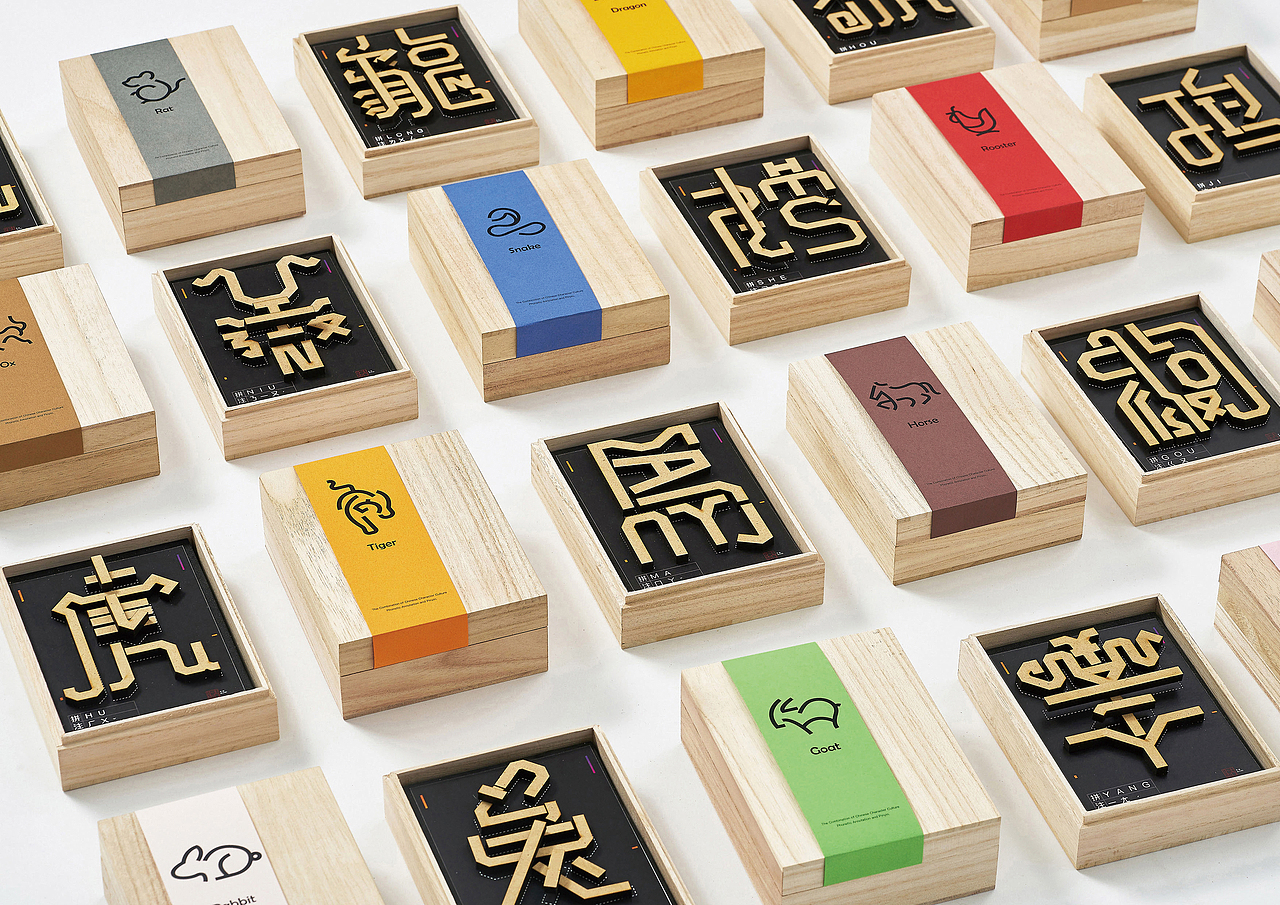
-透过文字再设计呈现两岸文化的连接与包容
We show cross-strait cultural connection and inclusiveness through ideogram redesign.
汉字在中国大陆与台湾之间不仅存在简繁字型之分,其分别所使用的拼读音法系统也有著一定的差异。选取大陆——罗马拼音、台湾——注音作为设计元素,以两岸共有的中华传统文化“十二生肖”为字型框架,并融入各个生肖的象形特徵,通过设计再造创意字体,借由汉字串联拼音与注音,传递汉字的包容性、可能性及表意文字的魅力。
我们将12组创意字体延伸为文教用具,每组用具含有特定的汉字笔划木块,搭配说明卡片引导观者进行互动拼装,在这个过程中眼/手/脑同时合作进行,不仅明白12组字体的组合逻辑,也能够从中学会拼音与注音书写形态,透过设计的力量,让两地之间有更加深层的认知与互动,也希望让更多非汉字地区的人瞭解到中华文化。